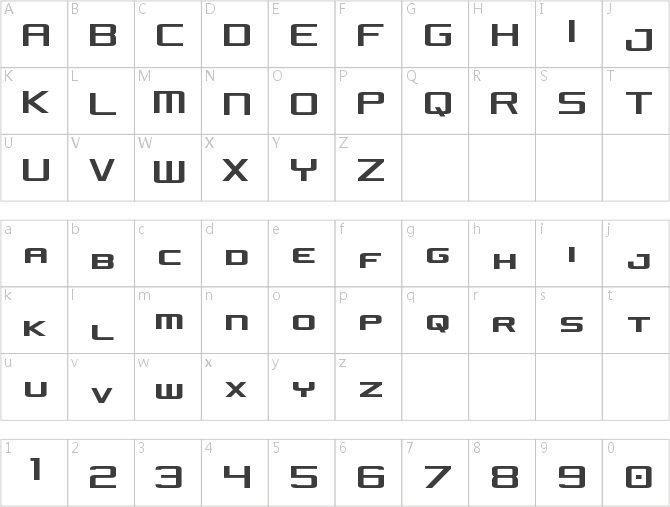
Concielian Jet Condensed 詳情頁(yè)
Concielian Jet Condensed字體字庫(kù)是一款讓人賞心悅目、百看不厭的英文字體,適合各類廣告和產(chǎn)品包裝設(shè)計(jì)應(yīng)用,字體大小0.02MB,格式為ttf字體,上傳用戶是伍佰,作者/版權(quán)方為未知